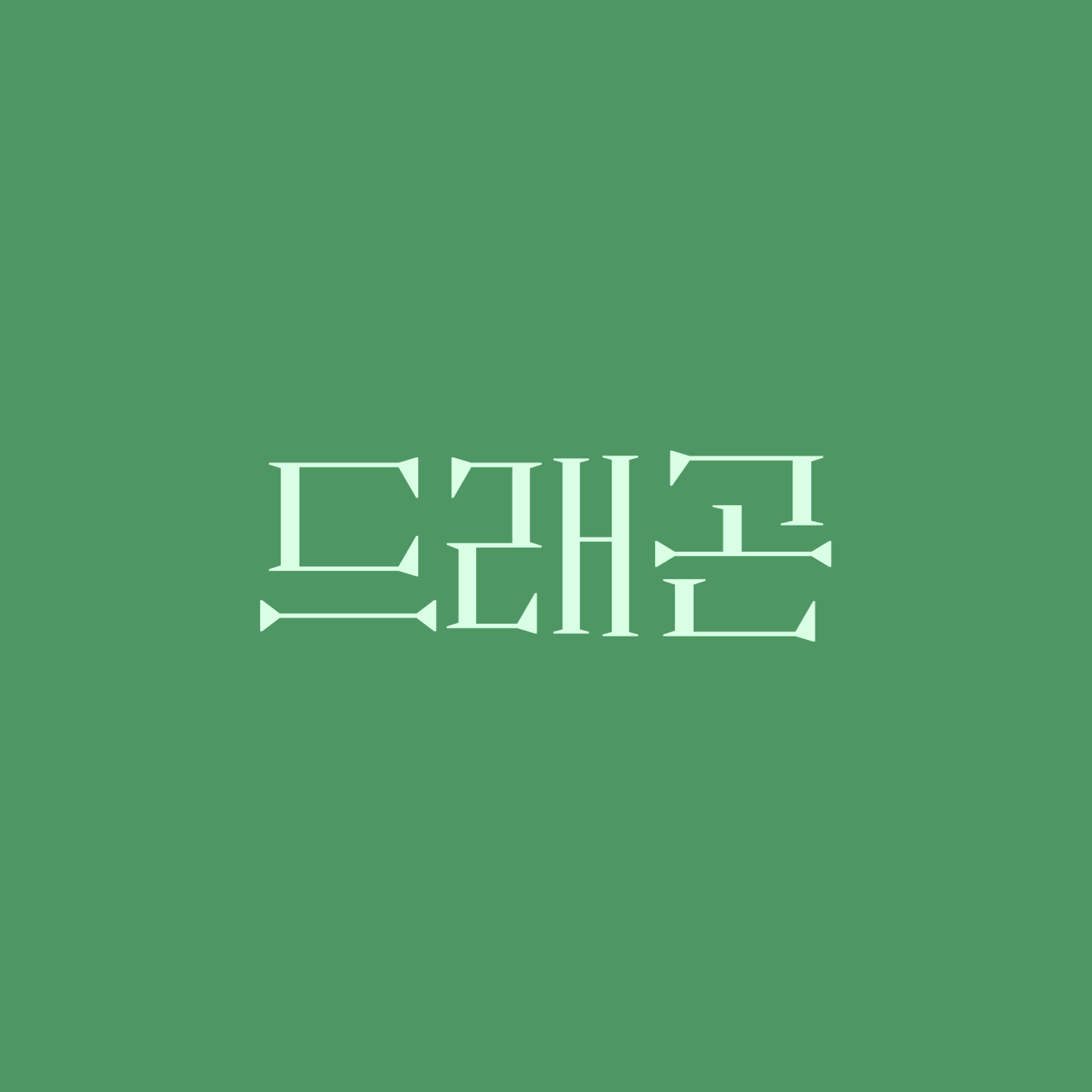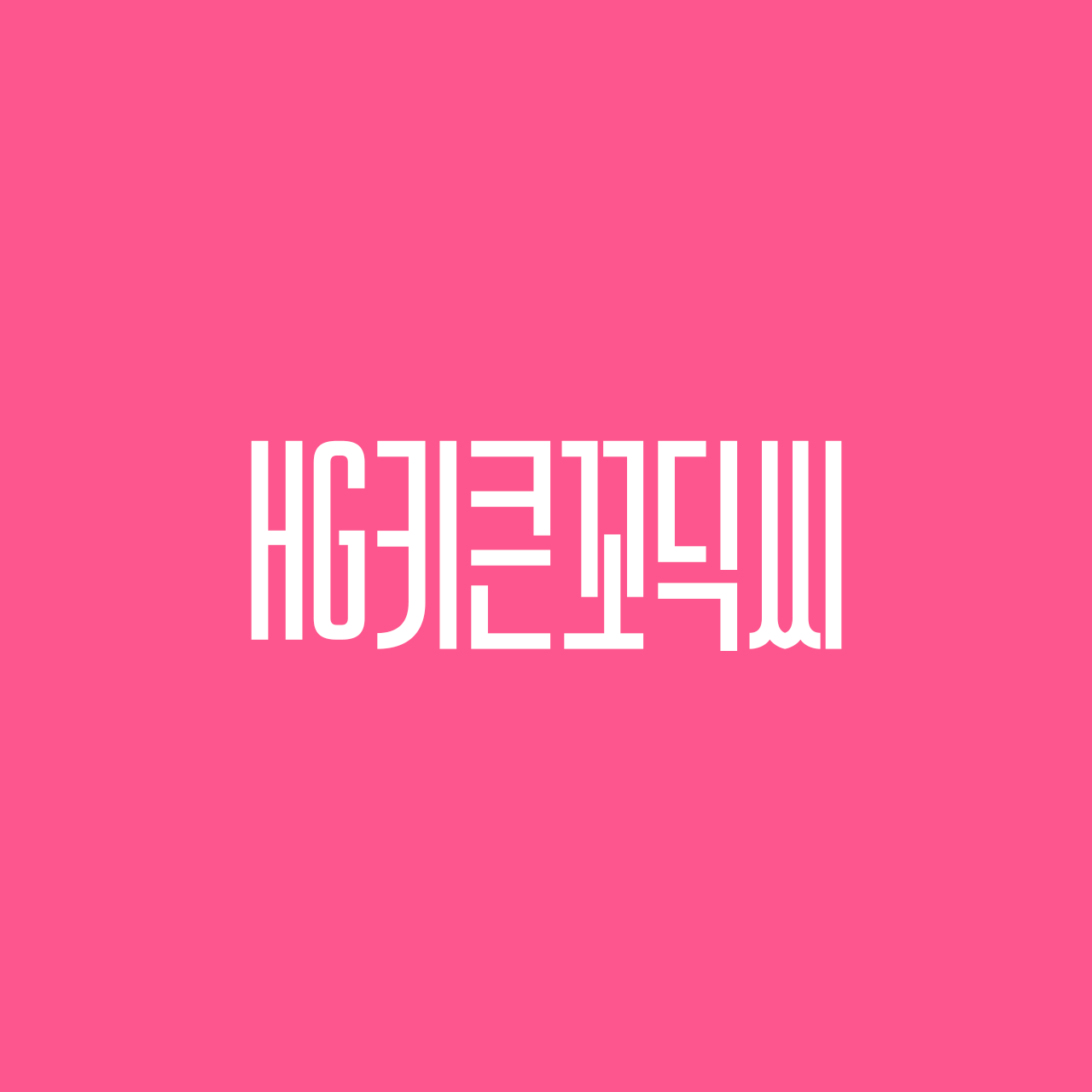
이벤트 포스터, F&B 패키징, 영상 타이틀, 책 표지 디자인까지
2025년에 특히나 많이 쓰이고, 많이 보였던 폰트를 한자리에 모았습니다.
어떤 프로젝트에서 어떤 폰트를 통해 필요한 분위기를 완성시켰는지,
다채로운 사용 예시와 함께 소개합니다.
지난해에 이어 올해도 ‘자소에 유기적인 포인트를 더한 폰트'들이 꾸준한 인기를 끌었습니다.
리듬감 있는 곡선들은 다양한 디자인에 감각적인 무드를 더해주죠.
누타입
NU 하바네라
《여름은 고작 계절》, 《겨울은 고작 계절》 표지 (출처: 위즈덤하우스)
2025년 산돌구름에 새롭게 입점한 파운드리 누타입의 첫 출시작 중 하나죠. 「NU 하바네라」는 정열적인 플라멩코 춤에서 영감을 받았다고 하는데요, ㅈ, ㅅ 등의 자소 디테일에서 그 감각이 뚜렷하게 드러납니다. 끊기지 않는 선율처럼 유연한 자소 구조가 특징으로, 특히 책 표지 디자인에서 강한 존재감을 발휘하며 베스트셀러 타이틀에 큼직하게 쓰여 눈길을 사로잡았습니다.
산돌
SD 프시케
2025 지역문화 활성화 사업 『당신의 문장이 기획이 될 때』, 포스터 (출처: 동작구, 동작문화재단)
부드러운 곡선미로 엘레강스한 분위기를 자아내는 「SD 프시케」는 2025년, 우아하고 클래식한 분위기가 필요한 순간마다 빠짐없이 등장한 폰트입니다. 특히 각종 이벤트를 알리는 포스터에서 그 진가를 발휘했는데요. 자칫 고전적으로 보일 수 있는 인상이지만, 어떤 효과를 주느냐에 따라서 화려하고 엣지 있는 반전 매력을 뽐냅니다. 흐름이 살아있는 이탤릭 웨이트를 활용하면, 디자인에 확실하게 생동감을 불어넣을 수 있죠.
한글만의 매력 중 하나는 극단적으로 단순하고 기하학적인 구성이 가능하다는 점인데요. 올해는 직선, 원, 삼각형을 활용한 대담하고 실험적인 자소 표현이 특히 주목받았습니다. 과감한 비례를 활용해 보는 재미를 더해주는 폰트들을 소개합니다.
탱타입
놂
《대리전》 표지 (출처: 다산책방)
「놂」은 한글 자소를 기하학적 도형처럼 해체해, 마치 미래의 암호와 같은 인상을 주는 폰트입니다. 듀나의 SF 소설 《대리전》 커버에서는 네온 핑크, 블루, 옐로우의 과감한 배색과 만나 사이버펑크적인 미감을 극대화했는데요.
직선과 원으로 이루어진 단순한 조형은 우주를 유영하는 오브제와 절묘하게 어우러지며, 키치하면서도 날카로운 퓨처리스틱 무드를 완성했습니다.
티랩
Tlab퓨처
2025 10CM ‘Centiner MEMBERSHIP’ 이벤트 〈올해는 내려나 봄〉 포스터 (출처: 씨에이엠위더스)
베리어블 폰트로 진화하며 한층 더 다양한 굵기로 표현이 가능하게 된 「Tlab퓨처」. 속공간이 큰 ‘ㅎ’, 과감하게 도드라진 ‘ㅇ’, 시원한 사선으로 뻗은 ‘ㅅ’은 그 자체로 강력한 인상을 남깁니다. 10CM의 포스터 사례처럼 이미지와 텍스트가 꽉 찬 구성에서도 다이내믹한 리듬감을 잃지 않는데요. 실험적인 조형미와 대중적인 트렌드를 동시에 잡은, 올해 특히 사랑을 많이 받았던 폰트입니다.
폰트가 가장 생생하게 기능하는 분야 중 하나는 단연 F&B인데요. 올해는 특히 식욕을 자극하는 붓글씨 계열 폰트가 두각을 드러냈습니다. 두툼하고 탄력 있는 획의 질감이 면발의 쫄깃함이나 매운맛의 강렬함을 시각적으로 전달해줍니다.
스튜디오좋
K110 쿠로코체 요세
『도쿠시마 라면』 패키징 (출처: 세븐일레븐)
일본의 전통 폰트인 에도모지, 그중에서도 요세모지(寄席文字)의 미감을 한글로 재해석한 「K110 쿠로코체 요세」는 일본 음식 패키지 디자인과 완벽한 합을 보여줍니다.
세븐일레븐의 『도쿠시마 라면』 패키지에서는 폰트의 두툼한 양감이 쫄깃한 면발이 강조된 사진과 어우러져 타이포그래피만으로 식욕을 돋우는 역할을 톡톡히 해냈습니다.
산돌
Sandoll 목단
『CU 화끈시리즈』 패키징 (출처: CU)
「Sandoll 목단」 은 묵직한 붓의 터치와 꽉꽉 들어찬 구조가 돋보이는 붓글씨 폰트입니다. 이러한 특징은 강한 맛, 특히 매운맛을 직관적으로 전달해야 하는 식품 패키지에서 최적의 시너지를 냈는데요.
획 하나하나에 담긴 역동적인 에너지는 자극적인 맛을 생생하게 시각화하며, 매대에 진열된 수많은 제품 사이에서 소비자의 시선을 단숨에 사로잡았습니다.
한동안 큰 획대비와 부리를 가진 구조의 폰트가 사랑받았다면, 올해는 오히려 민부리에 가까운 형태에서 큰 획대비를 더해 섬세한 감성과 모던함이 드러나는 폰트들이 주목받았습니다.
『《메리 제인의 모험》 표지 (출처: 김영사)
「210 드래곤」은 삼각형 요소의 예리함과 단단한 구조가 만나 독보적인 인상을 만드는 폰트입니다. 클래식한 느낌이 판타지나 유럽풍 디자인에 깊이를 더해주는데요. 특히 《메리 제인의 모험》 커버 타이틀에서는 고전적인 느낌과 현대적인 세련미가 공존하는 매력을 보여주었습니다. 가볍고 깔끔한 ExtraLight부터 강렬한 매력의 Heavy 웨이트까지, 탄탄한 패밀리 구성 덕분에 다양한 매체에서 활약 중입니다.
한글씨
HG키큰꼬딕씨
『72시간 소개팅: 홋카이도, 그리고 그 후』 포스터 (출처: 블랙페이퍼)
좁은 너비가 매력인 「HG키큰꼬딕씨」는 출시된 지 10년이 지났음에도 올해 다시금 디자이너들의 선택을 받고 있습니다. 특히 획 대비가 큰 Contrast 웨이트의 과감한 획 굵기 차이가 만들어내는 텐션은 영화 포스터 등 감성이 필요한 매체에서 확실한 존재감을 발휘했죠.
2025년의 폰트 트렌드를 관통하는 키워드는 ‘감각의 확장’입니다.
과감한 조형적 시도들과 부드러운 곡선 표현, 나아가 식욕을 돋우는 공감각적 타이포그래피가 시장을 주도했습니다. 또한, 획의 대비가 두드러지는 폰트가 주목받은 흐름 역시 올해 놓칠 수 없는 포인트였습니다.
내년에는 또 어떤 타이포그래피의 물결이 찾아올지, 기대되지 않나요? 우리 모두의 창작이 더욱 풍성해지기를 바라며, 지금까지 올해를 빛낸 폰트들을 소개해드렸습니다.